徐学成,新中国第一代字体设计师,中文字体设计历史的见证者,汉字印刷字体书写技艺非物质文化遗产传承人。
在去年,在中国字体设计界有一颗巨星陨落了,这是设计界乃至全中国的一个巨大遗憾,他就是徐学成先生。大家对于这个名字可能有一些陌生,徐学成先生是新中国的第一代字体设计师,可以算得上是中国字体设计界的老祖宗了。这一篇文章,我们希望通过介绍徐学成先生,给大家捋一捋中国字体设计的那一段开荒历史。
1984年,1983-1984年度文化部科技成果二等奖
1984年第一节全国印刷新字体评选会二等奖、三等奖
1987年日本森泽国际排版文字字体竞赛佳作奖
1987年国家标准局科学技术进步奖一等奖
2000年担任「北大方正」第一届、第二届汉字印刷字体大奖赛字体设计专家评选委员会委员
2011年上海市非物质文化遗产项目代表性传承人
徐学成先生的成就远远不是这些奖项可以衡量的,当年他与他的老伙计们,从零开始,对汉字字形的简化与规范,对汉字的字体设计进行摸索、探究,这些行为更能代表他对中国设计界乃至是中国文化事业不可磨灭的贡献与成就。
徐学成1928年出生于江苏武进的一个农村家庭,1952年进入了苏州美专深造,学习美术,在学校里,徐学成接触到了美术字,学校的学生会宣传干事要写横幅,那个年代的横幅一般用的都是美术字。一开始徐学成觉得自己写不好,不敢写,于是他就去帮美术字写得好的同学剪贴横幅,在剪贴的过程中偷偷学习了他们美术字的结构,哪些字要出格,哪些字怎么写,徐学成的美术字基础就是这么偷偷摸摸打下的。在毕业之后,徐学成进入了上海的人民出版社,上海人民出版社出版的一般都是政治读物,没办法像别的书籍一样设计得很花里胡哨,一般只能用字体作为封面,那么徐学成的美术字在这里就发挥作用了。由于是书籍上的字体,还是比较正式的政治书籍,所以徐学成对待这些封面字体十分讲究,碰到不熟悉或者难写的字,会去查铅字(也就是以前铅字排版的正文字体),因为铅字的骨架搭得比较好。徐学成的美术字也因此越写越好了。
△ 1959年莱比锡国际书籍装帧展部分获奖作品
△ 1960 年文化部改进和设计新字体文件
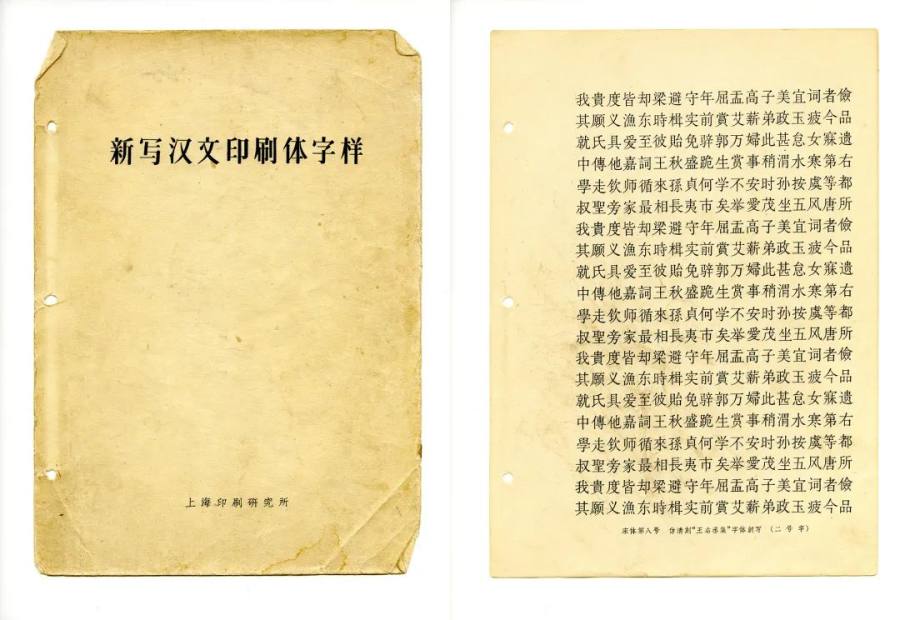
△ 1961 年《新写汉文印刷体字样》,徐学成设计宋体八号